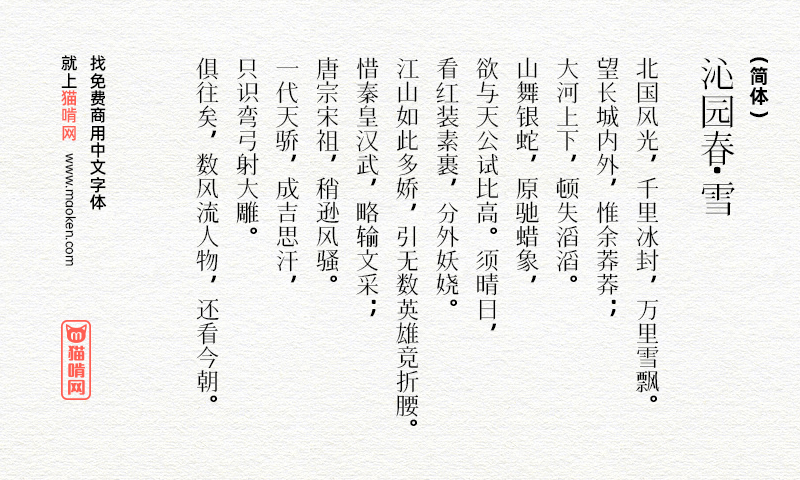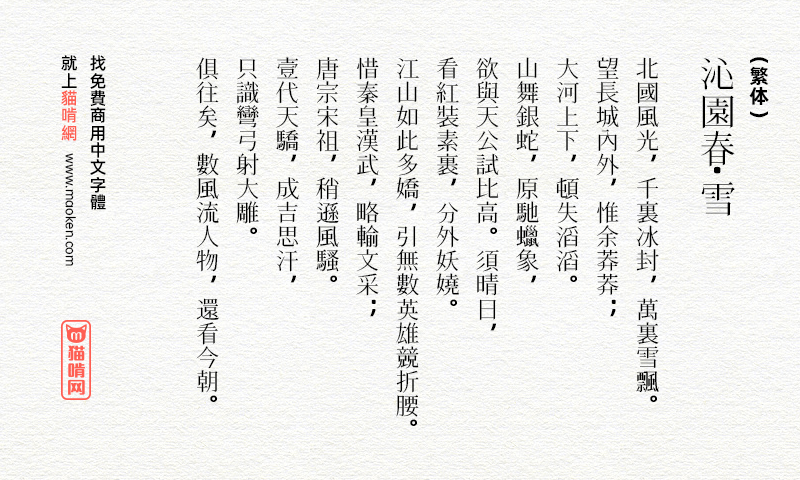
花园明朝体:几乎收录了所有汉字字形的免费开源字体
字体作者:GlyphWiki (日本) 字体字重:1个
花園フォント(花园明朝, 花园宋体,Hanazono Mincho,HanaMin)是一款基于日语的自由开源汉字字体,也是 GlyphWiki Project 的一部分。这款字体的特点是涵盖了目前 CJK (中日韩统一表意文字)字库中几乎所有的汉字与字符, 而且作为开源项目,任何人可自由下载使用。
「花园明朝 」 是一款免费字体,为 GlyphWiki 所开发,字形数量共 45090 + 47186 个,几乎收录了所有汉字字形。缺点是字形以日本字形为准,有一些字不符合中文书写规范。